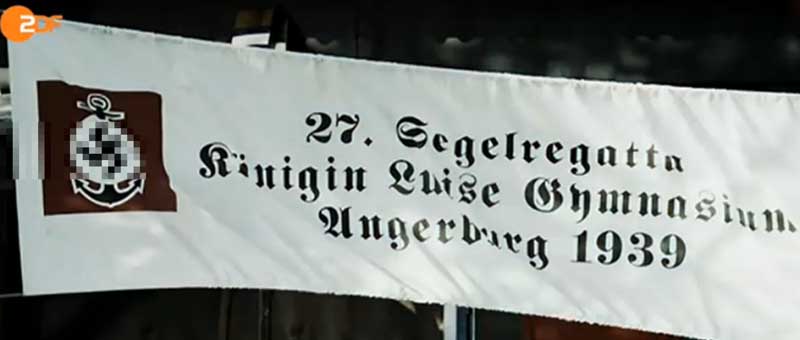
Langes s in heutigen Texten in gebrochener Schrift – notwendig, möglich oder unsinnig?
Naja, Verblödung für bestimmte Satzweisen in den Raum zu stellen ist nicht gerade besonders relativierend oder eine Aussage, die keine Besprechung provoziert. Und mir zuliebe musst du in solchen Fachfragen auch nichts relativieren oder unterdrücken. Ganz im Gegenteil: wenn solche starken Thesen aufgestellt werden, dann erwarte ich auch, dass man sie klar begründen kann und dies auch tut.
Du kannst Schreibungen, die früher™ üblich waren ja persönlich gerne präferieren, aber nur weil sie heute nicht mehr üblich sind, sind sie kein Zeichen von Verblödung. Ganz im Gegenteil: übliche (und damit im der Masse bestmöglich lesbare) Schreibweisen zu verwenden, folgt dem alten Sprachpfleger-Prinzip »die Schrift dient dem Leser«.
Zunächst waren sie »früher« nicht einfach üblich, sondern richtig. Und es gibt bisher keinen Tag X, an der diese Richtigkeit außer Kraft gesetzt wurde, was impliziert, daß die andere Schreibweise eben falsch ist. Indem man ihrer Verbreitung Vorschub leistet, nimmt man in Kauf, daß zunehmend solche Anachronismen kursieren:
Und die sind ja nun wirklich Ausweis von Bildungslücken, im Beispiel zufällig nicht nur orthographischer, sondern auch typographischer Art.
Mit jeder gesetzten Schrift wird sichtbar, wer für wen setzt. Wenn das lange s in einer Gotischen oder Fraktur nicht verwendet wird, hält entweder der Setzer den Leser nicht für gescheit genug dafür oder ist es selbst nicht. Das nimmt der Leser zur Kenntnis oder nicht, nach seinem Wissen. Je mehr »Massen« vom Massenmedium angesprochen werden, desto weniger gescheit geht es zu, auf beiden Seiten.
Von gescheit oder Bildung würde ich da gar nicht reden – Konventionen sind imo eher angebracht. Wenn man etwas als falsch oder richtig erklärt muss man in der Regel auch das Regelwerk dazu nennen. Ein gottgegebenes, allgemeingültiges Regelwerk wird sich schwer finden lassen … gerade in der Orthografie und Typografie.
Das meine ich tatsächlich nicht. Ich habe viele Jahre für Feuilletons geschrieben. Da habe ich die Erfahrung gemacht, daß es Zeitungen und Redakteure gibt, die ihren Lesern deutlich weniger zutrauen. Sie halten ihre Leser immer für etwas dümmer als sich selbst. Da darf man dann keine Fremdwörter verwenden, die eventuell nicht zum aktiven Wortschatz eines jeden Mittdreißigers gehören.Und es gibt Zeitungen, die haben Respekt vor ihren klugen Lesern und versuchen, deren Ansprüche zu erfüllen. Die wissen, daß ihre Leser ggf. etwas nachschlagen, wenn sie es nicht verstehen.
Wenn man das lange s wegläßt, kann man ebensogut Bindestriche weglassen und Apostrophe vor Genitiv-s setzen. Eine passende Regel oder Begründung findet sich immer. Für anspruchsvolle Leser laßt man die Finger von allem, was deren Lesegewohnheiten stören könnte. Und gebildete, anspruchsvolle Leute können Fraktur lesen. Und damit meine ich keine Studenten oder junge Akademiker, sondern eben gebildete Leute, die nicht Reader, sondern Bücher lesen. Viele. So etwas gibt es. An die wendet sich der »Spiegel« nicht. Deshalb ist es auch schnurz, welche Buchstaben er auf seine Seiten setzt und ob er das Wort »dunkel« mit dunkler Farbe darstellt und das Wort »hell« mit heller oder noch schlechtere Ideen hat.
Und es gibt Zeitungen, die haben Respekt vor ihren klugen Lesern und versuchen, deren Ansprüche zu erfüllen. Die wissen, daß ihre Leser ggf. etwas nachschlagen, wenn sie es nicht verstehen.
Also selbst die Alte Tante F.A.Z., die sich ja dauernd rühmt, daß hinter ihr immer ein kluger Kopf stecke, hat das ſ in den gebrochenen Kommentarüberschriften abgeschafft, weil man meinte, der Leser könne solch intellektuelle Herausforderungen heute nicht mehr bewältigen. Eigentlich auch ein trauriges Menschenbild, wenn man es recht überlegt.
Und es gibt bisher keinen Tag X, an der diese Richtigkeit außer Kraft gesetzt wurde, was impliziert, daß die andere Schreibweise eben falsch ist.
Es entbehrt nicht einer gewissen Ironie, wenn gerade du hier auf »in Kraft gesetzte Regeln« pochen willst, wo du doch selbst die geltenden Regeln des 21. und ja teilweise sogar des 20. Jahrhunderts bewusst missachtest. Die geltenden Regeln/Konventionen von 2015 sind dir schnuppe, aber die von 1915 müssen komischerweise weiter angewendet werden – wenn nicht, ist es ein Zeichen der Verblödung. Eine höchst seltsame Logik! Und warum eigentlich die von 1915? Warum sind nicht die Regeln von 1915 ein Zeichen der Verblödung in ihrem Wandel weg von den Regeln von 1815 oder 1715? Ich frage dies immer wieder, aber überzeugende Antworten gibt es darauf keine. Wenn man das »Richtig« in der Historie sucht und nicht in der Konvention der Gegenwart, wo soll es dann sein? In welchem Buch? In welchem Jahr? Wer bestimmt das?
Diese konservative Sprachpflegerlogik bleibt ein Cherry Picking ohne Substanz. Irgendwie auf Biegen und Brechen willkürliche alte Konventionsstände rechtfertigen (die übrigens nur durch Wandel entstanden sind), aber dann weiteren Wandel ablehnen, der insbesondere zu den eigenen Lebzeiten passiert. Es ist einfach nicht schlüssig.
Und in der Sache stimmt dein Argument ja sowieso nicht. Die schriftstilbasierte Lang-s-Unterscheidung wurde Anfang des 19. Jahrhunderts verbindlich im Rahmen der deutschen Orthografie geregelt. Der Stand der letzteren änderte sich im Laufe des 20. Jahrhunderts etwas und wurde ab Ende des 20. Jahrhunderts schließlich stufenweise abgeschafft und durch eine neue Orthografie ersetzt. Die alte Rechtschreibung ist somit faktisch »außer Kraft gesetzt« und mit ihr sämtliche Regeln, einschließlich der schriftstilabhängige Orthografie und des langen s. Dieser Buchstabe ist schlicht nicht mehr existent in der aktuellen amtlichen Orthografie und daher kann die Nichtbenutzung auch im Sinne der heutigen Orthografie nicht falsch sein. Schreibungen in gebrochener Schrift ohne ſ sind nicht historisch, aber eben auch nicht falsch. So wie man in Antiqua 1815 meist noch ein ſ benutzte, 1915 dann aber in der Regel nicht mehr. Zeiten ändern sich. Ich bitte um sachliche Erklärung, warum in diesen 100 Jahren das ſ in der Antiqua verschwinden durfte (und du das heute auch so anwendest), aber in den folgenden 100 Jahren nicht aus der gebrochenen Schrift? Oder warum die alten Fraktursatz-Regeln nun gar für alle Zeit(?) weiter gelten sollen, wenn sich die Regeln doch in den letzten Jahrhunderten ständig veränderten. Was soll das Prinzip sein? Ich verstehe es nicht.
Das ist ein gutes Beispiel dafür, dass dieses Wissen auch ohne Verwendung auf einem Spiegel-Titel vorhanden ist – also keine Spur von Verblödung  :-o
Mich würde ja mal interessieren, ob es eine Erhebung gibt wievielen Menschen (nicht Setzern) die Regeln vor hundert Jahren klar waren, und wem ein falsch gesetztes s aufgefallen wäre ..?
... und das man als Intellektueller unbedingt regelmäßig Fraktur lesen muss um sich als solchen bezeichnen zu dürfen, halte ich für eine sehr steile These  8-)